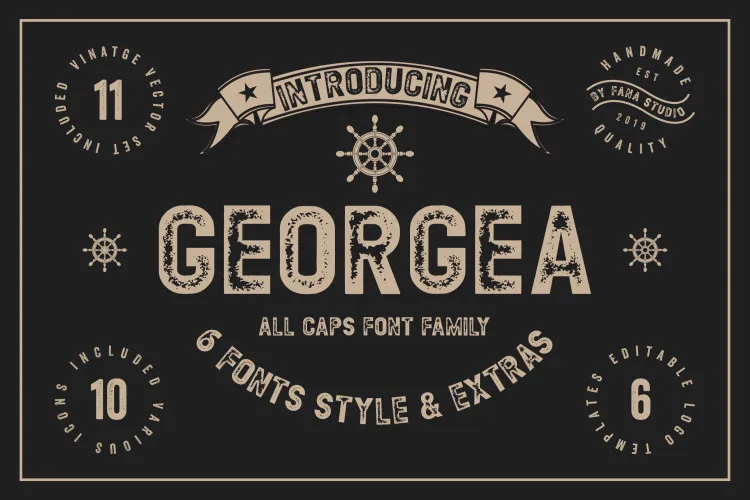
GEORGEA Typeface – Download Grátis
Esta é uma fonte sans-serif vintage com movimento elegante de letra à mão. Ela traz um aspecto clássico antigo, ideal para projetos atuais e futuros. Introduzimos a família Georgea All Caps, composta por Georgea, que se destaca como uma fonte sans-serif em todas as letras maiúsculas. Georgea é uma combinação perfeita de simplicidade e elegância, oferecendo versões comum e itálico. Além disso, inclui duas opções mais ousadas: outline e grunge. Totalmente compatível com OTF e TTF, Georgea contém seis arquivos de fonte para que você possa escolher o melhor para cada projeto. Esta fonte se destaca não apenas por sua estética distintiva, mas também pela versatilidade. É perfeita para criar identidades corporativas, logos, etiquetas de produtos, cartazes, rótulos de camisetas, placas e sinalização. Sem dúvida, Georgea é uma escolha sólida que revigorará seu design atual ou dará ao seu próximo projeto um toque único e moderno.